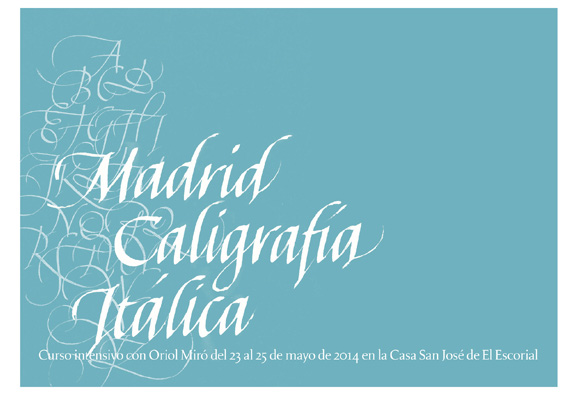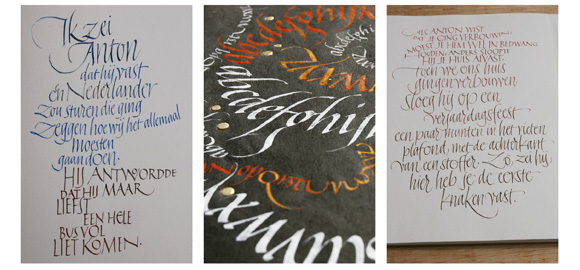
Buenas noticias para los amantes de las formas caligráficas. El prestigioso calígrafo catalán Oriol Miró va a impartir un curso intensivo de itálica en El Escorial.
Según nos cuenta él mismo: «Vamos a hacer itálica a tope, del 23 al 25 de mayo, durmiendo y comiendo entre tintas y plumas. Practicaremos la letra itálica cancilleresca en la tradición de los maestros renacentistas Arrighi y Cataneo. Escribiremos mañana-tarde-noche y hasta que nos salga el Arrighi por las orejas».